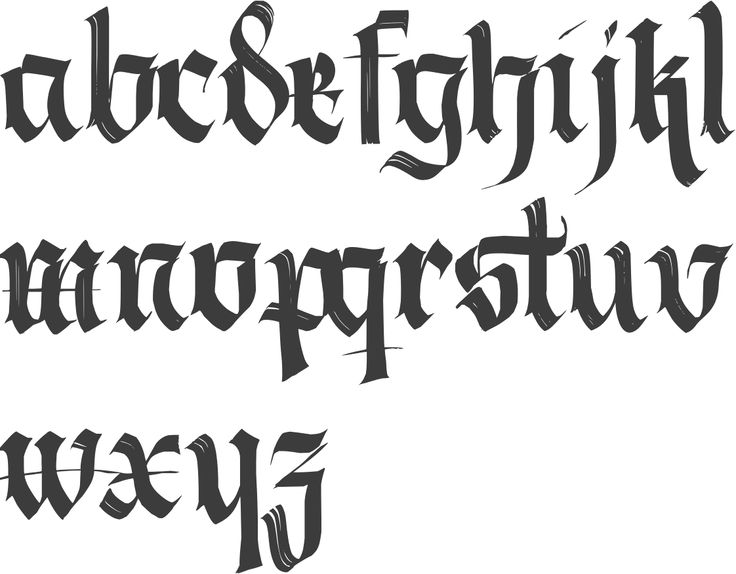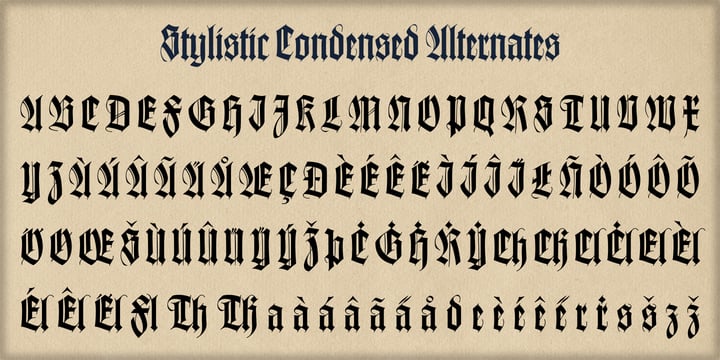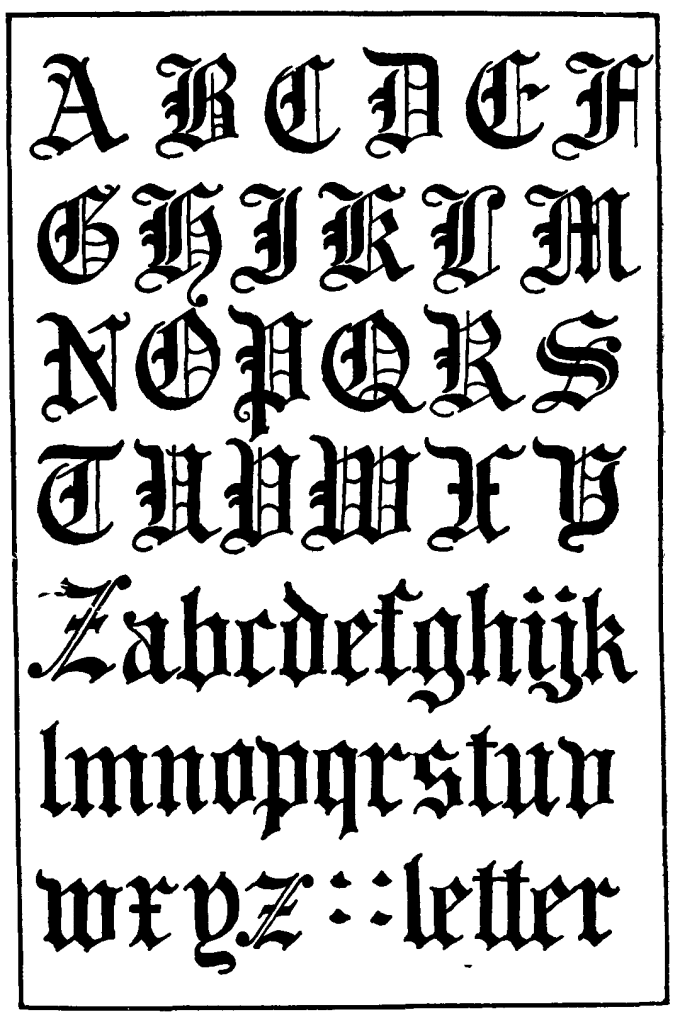
Какой шрифт выбрать для резюме
КарьераArial или Times New Roman? Оказывается, шрифт может стать зеркалом психики человека. Тому, какой вид выбирает соискатель для своих документов, рекрутеры придают особое значение.
Покажи, как ты пишешь — и я скажу, кто ты. Выбирая подходящего претендента на открывшуюся вакансию, многие работодатели проверяют отнюдь не только его профессиональные качества. Немало внимания обращается и на целый ряд других факторов — к примеру, на вид шрифта, которому соискатель отдает предпочтение при написании резюме. Оказывается, такая деталь может многое рассказать о психологии человека. Причем особое значение ей придается при рассмотрении кандидатуры на руководящий пост.
Чтобы «расшифровать» фасад резюме, рекрутеры обращаются к помощи графологов – специалистов, способных по почерку и виду используемого шрифта определить как свойства характера, так и психическое состояние личности. У немецких работодателей их услуги сегодня пользуются спросом.
За помощью к графологу
Одним из ведущих немецких экспертов в области графологии считается ученый, издатель, преподаватель Хельмут Плоог (Helmut Ploog), возглавляющий Объединение сертифицированных графологов-психологов. К услугам графологической практики, которой владеет этот опытный специалист, обращаются как частные лица, так и различные компании, медики, криминалисты, консультанты по кадровым вопросам. Одним клиентам эксперты подсказывают, как лучше оформить интернет-сайт, другим — какого специалиста принять на работу. Достижения науки, зародившейся сотни лет назад, продолжают оставаться востребованными и в цифровую эпоху.
Подпись может многое рассказать о человекеФото: Fotolia/Halfpoint Особенности психологии того или иного человека Хельмут Плоог может проанализировать даже по почерку. Дело в том, что, как уверяет графолог, подпись ставится не рукой, а подсознанием человека. И поэтому по характеру закорючек и завитков, силе нажима, направлению штрихов, другим подобным критериям профессионал всегда определит, тщеславны вы или скромны, заносчивы или относитесь к себе с самоиронией, наделены способностью работать в команде или предпочитаете трудиться в одиночку.
Допустим, размашистая подпись свидетельствует о вашей решительности, мелкая — об узкой специализации знаний, длинная — о последовательности в действиях, короткая – о чрезмерной импульсивности, волнистая — о дипломатичности, а обстоятельная, когда можно прочесть всю фамилию — о дотошности. Подпись может поведать о настроении человека, рассказать о состоянии его здоровья и даже выдать возраст и пол, поясняет в интервью сервисному порталу tt-bewerbungsservice.de Хельмут Плоог.
Ты мне, зеркальце, скажи…
Ну, а если глазам графолога предстанет ваша интернет-страница, то тут для его деятельности будет просто поляна. Как утверждают эксперты, электронные средства информации могут поведать о человеке не меньше, чем рукописные документы. Стиль, в котором оформлен веб-сайт, характер его иллюстраций, виды шрифтов, в которых набраны тексты, — подсказок для составления вашего развернутого личностного портрета более чем достаточно.
Вам нравится жирный шрифт? Значит, вы стараетесь скрыть свою индивидуальность, но при этом являетесь личностью с сильным, решительным характером.
Склонность к использованию мелкого шрифта говорит о вашей самодостаточности и отсутствии потребности выделиться. Буквы со строгим графическим рисунком предпочитают использовать мужчины, в первую очередь – авторитарные и непреклонные. Более округлые шрифты любят применять женщины, прежде всего — гармоничные, мягкие, человечные и склонные к компромиссам.
«В повседневной коммуникации вид выбранного шрифта зачастую недооценивается», — цитирует газета Süddeutsche Zeitung немецкого дизайнера и преподавателя полиграфии Нину Штессингер (Nina Stössinger). По мнению этого специалиста, при написании электронных писем и тем более заявлений о приеме на работу не следует ограничиваться шрифтами Arial или Times New Roman. Это все равно, что носить каждый день один и тот же костюм: выглядит скучно и непривлекательно. Соответствующее впечатление складывается и у потенциального работодателя. Лучше набрать текст шрифтом, позволяющим выделить резюме из общей массы и с ходу заинтересовать рекрутера, рекомендует эксперт.
Впрочем, есть компании, где централизованно устанавливаются типы и размеры шрифтов, которые следует использовать в различных видах документов. Например, производитель автомобильных комплектующих Continental избрал для себя в качестве стандарта шрифт Arial. В электронной почте автомобилестроительного концерна Daimler применяется шрифт Calibri, а в документах, представляемых на бизнес-презентациях — особые шрифты, разработанные специально для этой компании. В любом случае, до того как составлять резюме, претенденту на вакансию не мешает проконсультироваться по поводу признанного на данной фирме стандарта. Для соискателя это станет только дополнительным плюсом, уверяют немецкие эксперты.
Как пишутся немецкие печатные буквы и прописью
- Немецкие письменные шрифты
- Австрийские письменные шрифты
- Какой письменный немецкий шрифт использовать?
Если вы уже освоили письменный шрифт немецких букв — можно перейти к изучению печатного варианта, чтобы ваше письмо было понятным не только вам.
Для чего это нужно?
- Во-первых, записывая слова рукой, мы подключаем к процессу обучения моторную память. Это ценный ресурс при изучении иностранного языка, его обязательно надо задействовать!